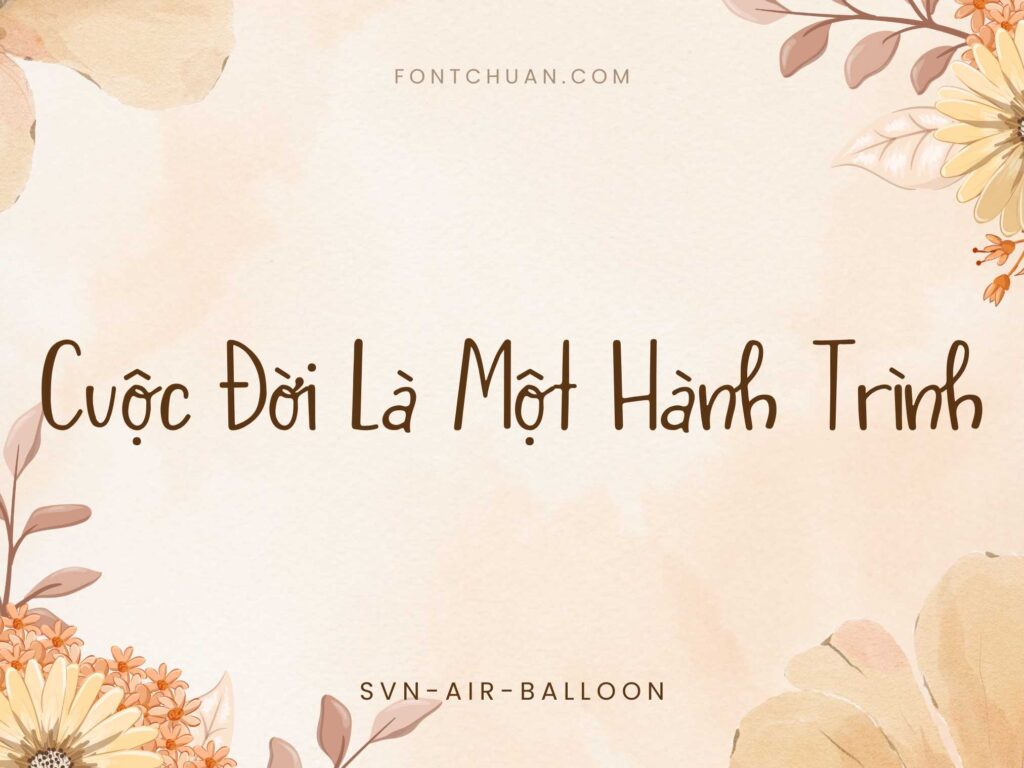
Font SVN Air Balloon Việt Hóa
Air Balloon là một font chữ viết tay đáng yêu và vui nhộn, được thiết kế bởi Misti’s Fonts. Font này mang phong cách thủ công, dễ đọc ở mọi kích cỡ, phù hợp cho nhiều mục đích sử dụng như thiệp mời, tiêu đề, áo thun và các dự án thiết kế khác. Với hơn 200 ký tự, Air Balloon cung cấp sự linh hoạt và sáng tạo cho các nhà thiết kế. Font đã được Việt hóa để hỗ trợ tiếng Việt bởi Styleno.1 Fonts, đồng thời hỗ trợ nhiều ngôn ngữ khác, giúp mở rộng phạm vi sử dụng trên toàn cầu. Font này được thành viên của Font Chuẩn sưu tầm và chia sẻ, đáp ứng nhu cầu của bạn đọc và ứng dụng thực tế vào các dự án thiết kế.
Đặc điểm thiết kế của Air Balloon bao gồm cấu trúc chữ mềm mại, độ tương phản nhẹ và các đường nét uyển chuyển, tạo nên sự thân thiện và thu hút. Font này phù hợp cho các ứng dụng như thiết kế thiệp mời, tiêu đề, áo thun và các sản phẩm quảng cáo. Các ngành nghề phù hợp bao gồm quảng cáo, sự kiện, giáo dục và nghệ thuật.